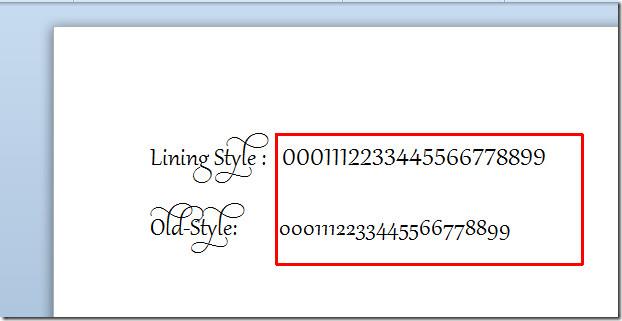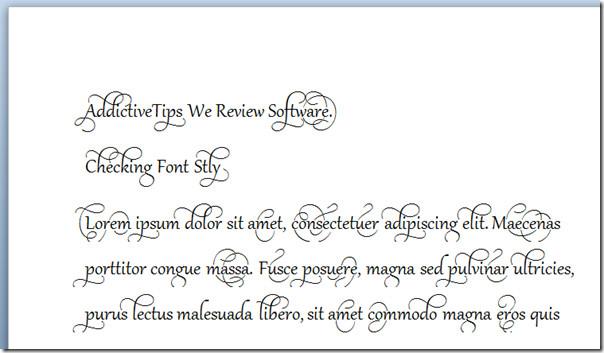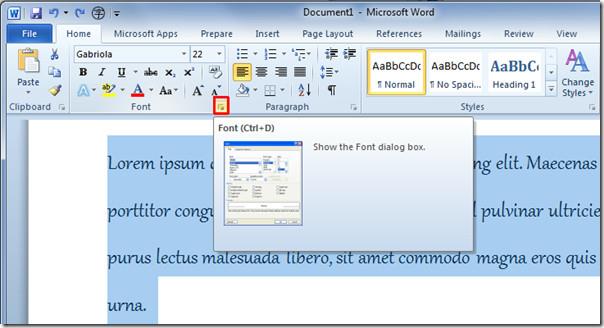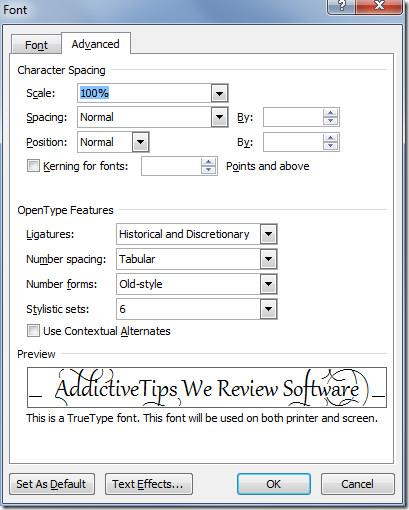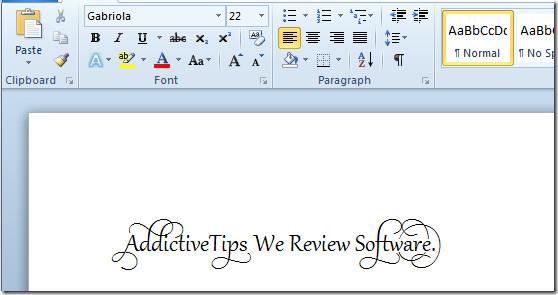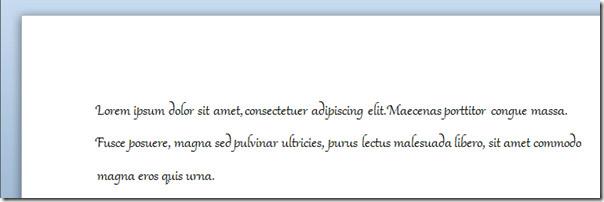
Word 2010 包含豐富的字體系列和字體樣式,除了基本字體樣式外,還包含一些進階連字樣式。您可能聽說過新推出的“連字”,它包含不同的風格集、數位格式和數位間距樣式,可以讓您的文件看起來更加華麗。在本文中,我們將重點放在如何在文件中應用這些連字風格集。
若要開始使用新的字體樣式和連字,請開啟需要套用不同字體樣式的 Word 2010 文件。為了演示,我們在文件中添加了Lorem Ipsum文字。
導覽至「首頁」標籤,在「字型」群組中,選擇Gabriola字型系列。選擇要套用不同樣式集的文本,然後點擊「字體」群組右下角的小按鈕。
它會打開“字體”對話框。在「OpenType 功能」下,您將看到許多樣式、設計和連字。在“連字”中選擇“歷史和自由連字”,在“數字間距”中選擇“製表符”。選擇“數字形式”樣式,最後選擇“風格集”。您將在預覽窗格中看到所選文字的預覽。點選“確定”。
選定的文字被更改為指定的連字和風格集。
現在我們將對文字套用其他樣式設定。右鍵單擊選定的文本,然後按一下“字體”。
系統會彈出「字體」對話框,現在請將不同的字體樣式套用到文字上。點選“確定”繼續。
指定的連字樣式將會套用至文字。
現在開始書寫,它將在您打字時自動套用連字樣式。
除了字母樣式外,它還包含不同的數字字體樣式;Old 和 Lining 樣式。